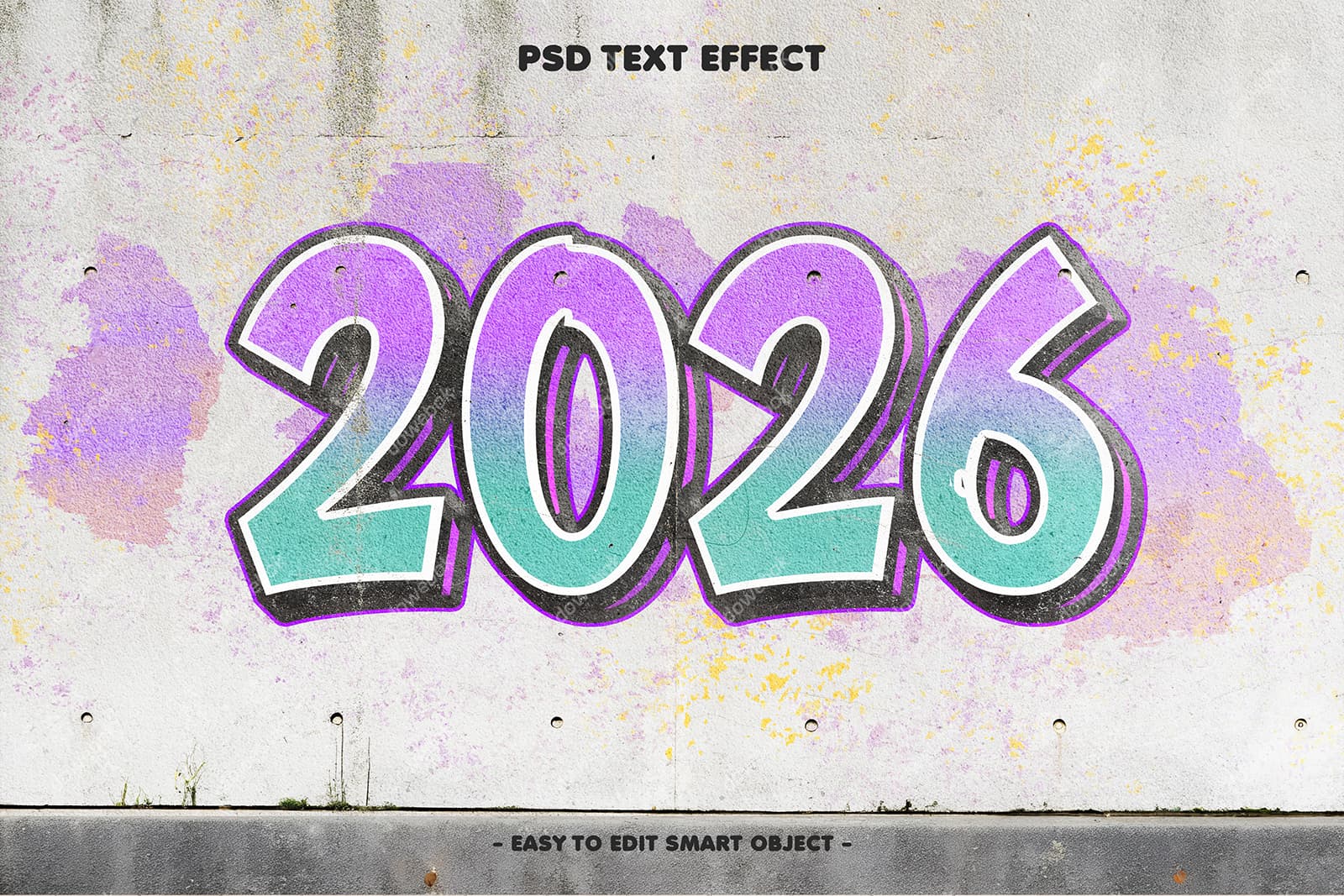
这是一款由涂鸦数字设计的 2026 新年快乐背景素材,斑驳的灰白墙面为背景,点缀紫黄泼墨痕迹,“2026” 以紫绿渐变的涂鸦字体呈现,边缘粗犷且富有街头质感,上方标注 “PSD TEXT EFFECT”,底部说明 “EASY TO EDIT SMART OBJECT”。整体风格随性张扬,涂鸦元素与泼墨背景结合,既显潮流个性,又突出字体效果的可编辑属性,适配创意海报、潮流物料等场景。